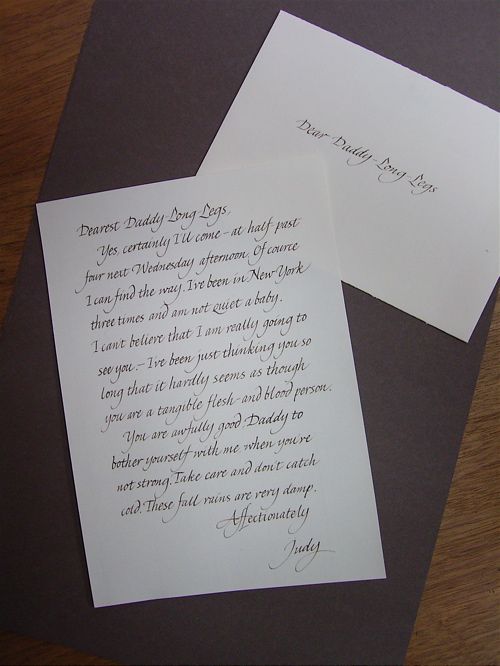
あしながおじさん
クラスでは、handwritingもイタリック体の中で学びます。
昔、中学校でやった筆記体(多少形が違う部分がありますが)のような感じです。
最初は通常のイタリック体の形を取りますが、徐々にその人なりの文字になっていける様にしていきます。own handということです。
クラスのKeikoさんは、こんな素晴らしい手紙を書いてきてくれました。あしながおじさんの一節です。
初めておじさんに会うときのJudyの手紙だそうです。文章もとってもいい感じなんですよ。
手書きの手紙は、何語で書かれていようと素敵です。ホントいいなぁ・・・
何気なく検索していたら・・・こんな素敵なページにあたり、とても素敵なカードに見とれておりました。
とても優雅な字体で流れるような線だけで、こんなにも
美しい一枚のカードになるのですね。
本当に、素敵の一言に尽きます。
カリグラフィーって、色々な事のに幅を広められ・・・
私も、俄然、興味を持ちました。
作品を透して、作者の人が見えてきそうで・・本当に奥深いのですね。
そうそう、そうなのです!
手書きも文字から、その人が見えてくるのですよね。一生懸命書いている人の文字からは、その熱心さが伝わります。